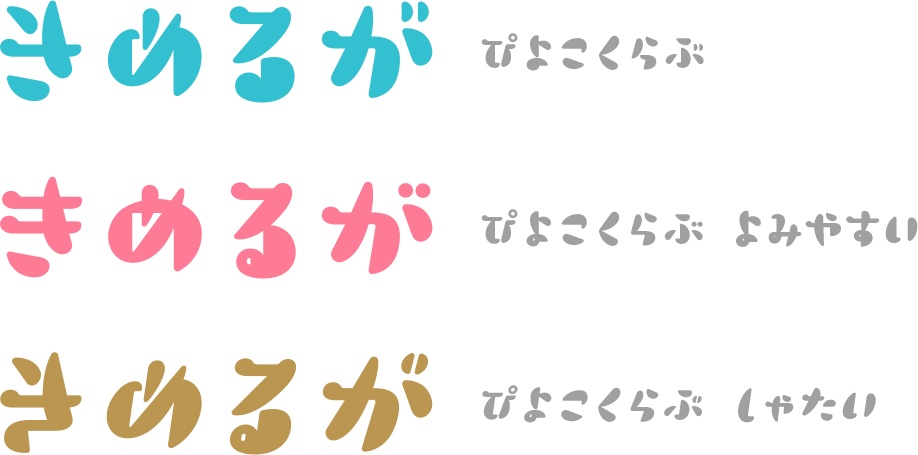
ぴよこくらぶ フォント
シンプルで幾何学的な線で描かれつつも、どこか愛らしいフォント。ロゴタイトルやキャッチフレーズなどの大きなサイズでの使い方に適しています。 「ぴよこくらぶ」「ぴよこくらぶ-よみやすい」「ぴよこくらぶ-しゃたい」の3つのフォントが収録されています。 動作環境 Mac:システム/OS X対応(10.x)〜最新のOS X Windows:OS/日本語版Windows2000、XP、VISTA、Windows7〜11以降 フォント形式:OpenTypeフォント 収録文字数について ひらがな、カタカナのみの書体になります。 安心して使えるロイヤリティフリーの書体 あらゆる商用・デザイン用途(印刷物・ゲーム・アプリ・映像・動画・ロゴ・同人作品)に使用できる、商用申請の必要のないロイヤリティフリーの書体になります。文字の加工・変形も可能です。ご安心ください。